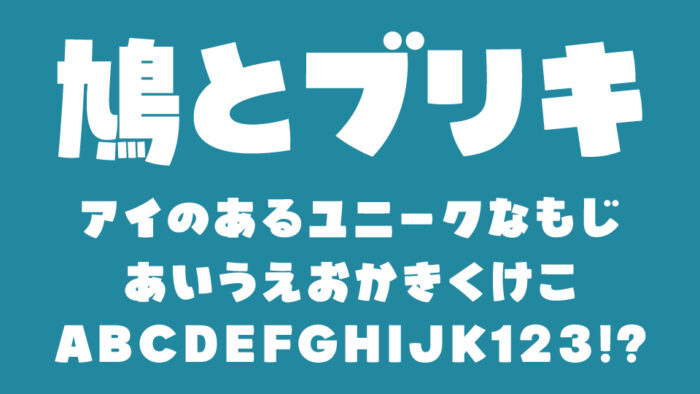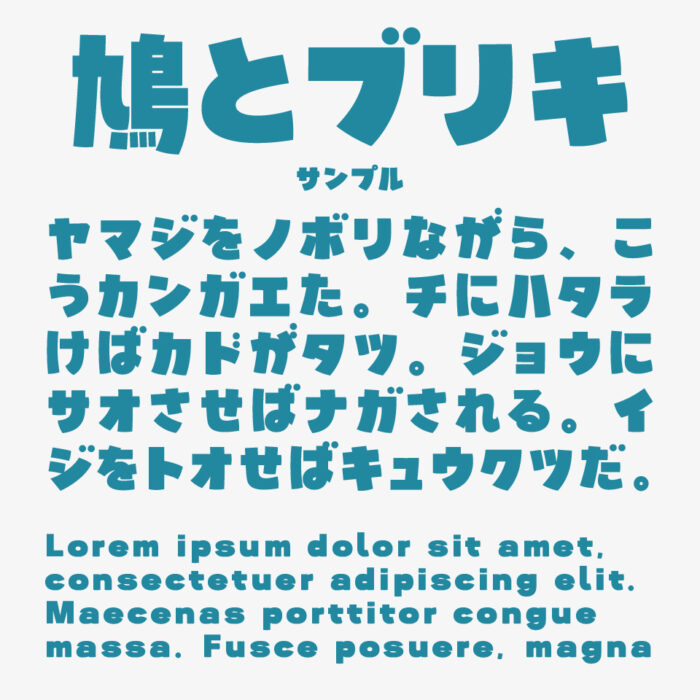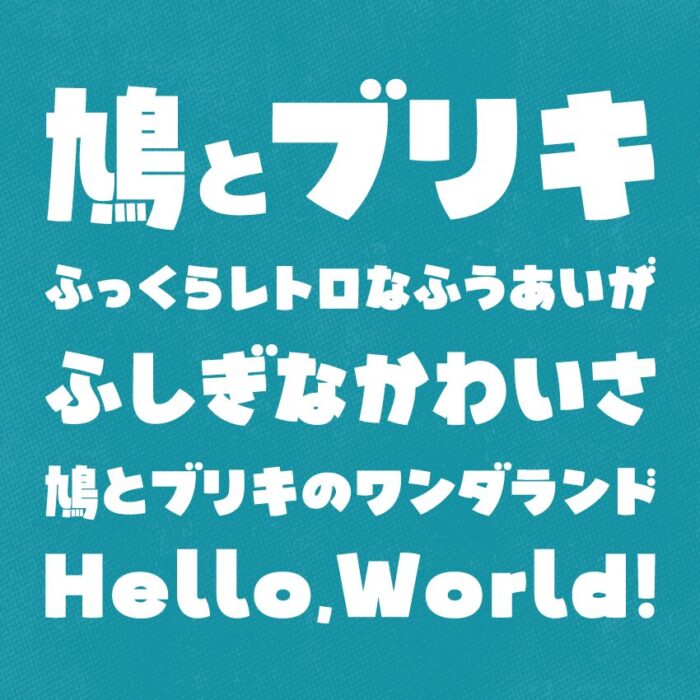
鳩とブリキのワンダランド
鳩とブリキのワンダランドフォントは、極太な重量感とポップさが共存する、レトロな風合いが可愛らしいデザインフォントです。
骨太でどっしりとしたシルエットに、わずかに斜めや傾きのある文字バランスが加わり、手作りの温もりと勢いが感じられるデザインです。フォント名も昭和レトロな味わいのあるとってもステキでオシャレな名前です。
ふっくらとしたエレメントが手書きぽさもあり、細部までかわいいフォントです。
収録文字は、ひらがな・カタカナ・アルファベット・数字・記号が収録されています。